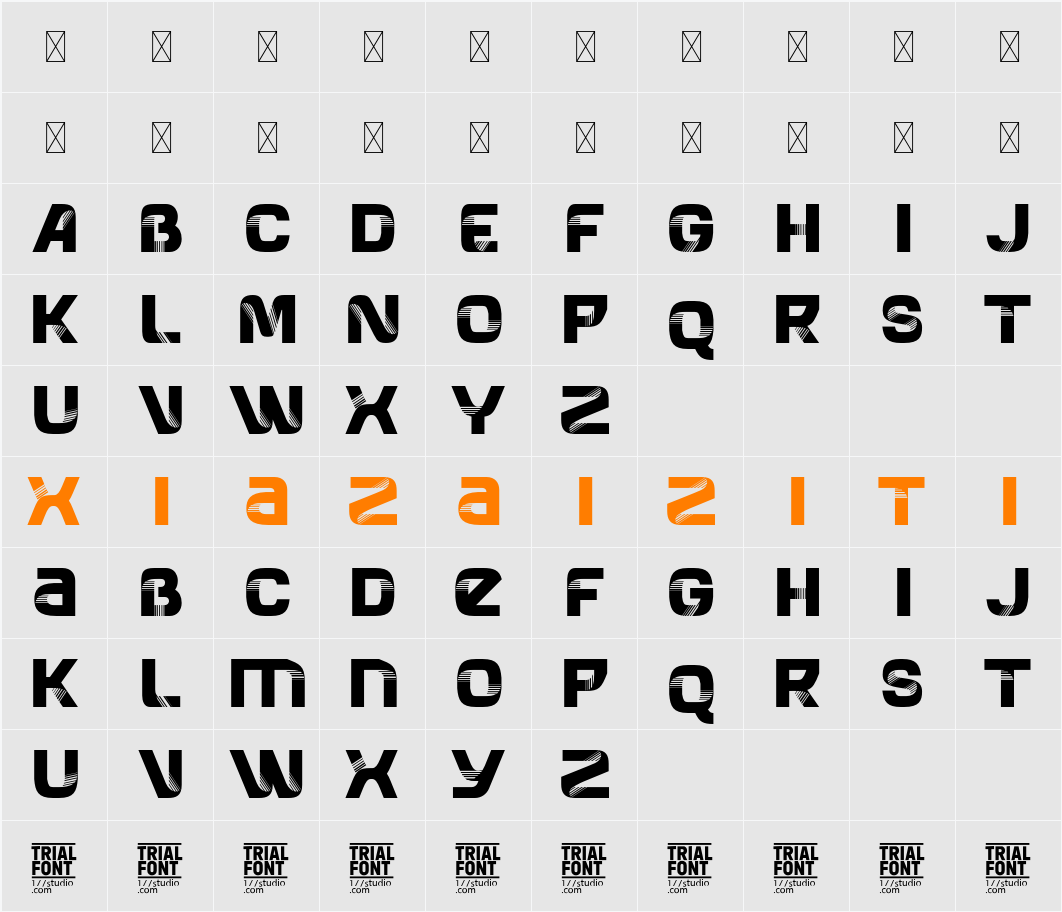
Wisdom Defense Demo
Wisdom Defense Demo,这款字体结构工整、笔画清晰,兼顾美观与易读性,适用于标题、正文、海报、包装、LOGO 等多种场景。字形优雅稳定,风格百搭耐看,适配日常排版与创意设计,让文字呈现更舒适、更具质感。Wisdom Defense Demo一笔一画,皆是细节,以均衡的比例、流畅的线条打造舒适视觉体验,字形端正大气,风格简约现代。无论是商业设计、品牌宣传还是日常排版,都能轻松驾驭,让文字更有格调与力量。Wisdom Defense Demo字体下载。